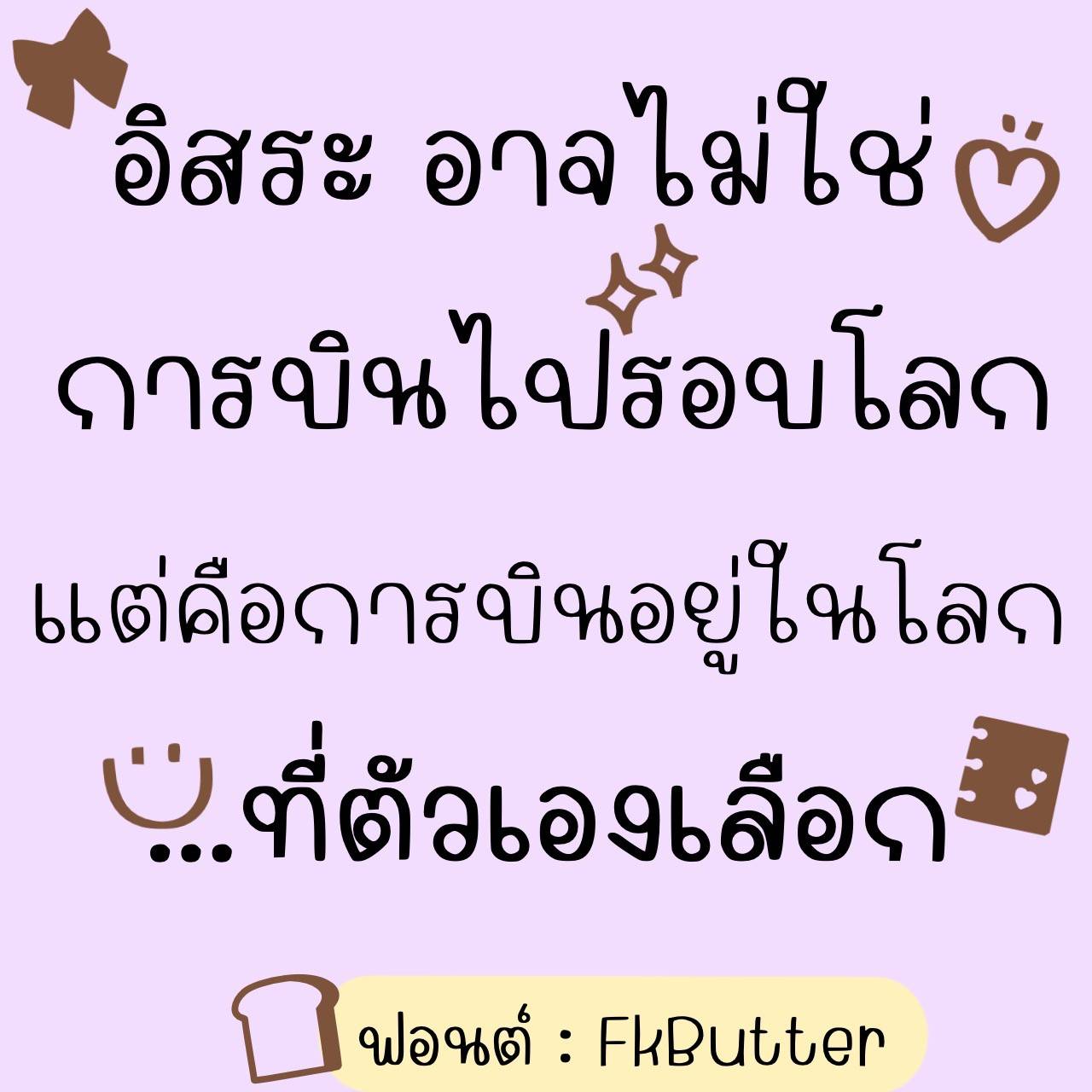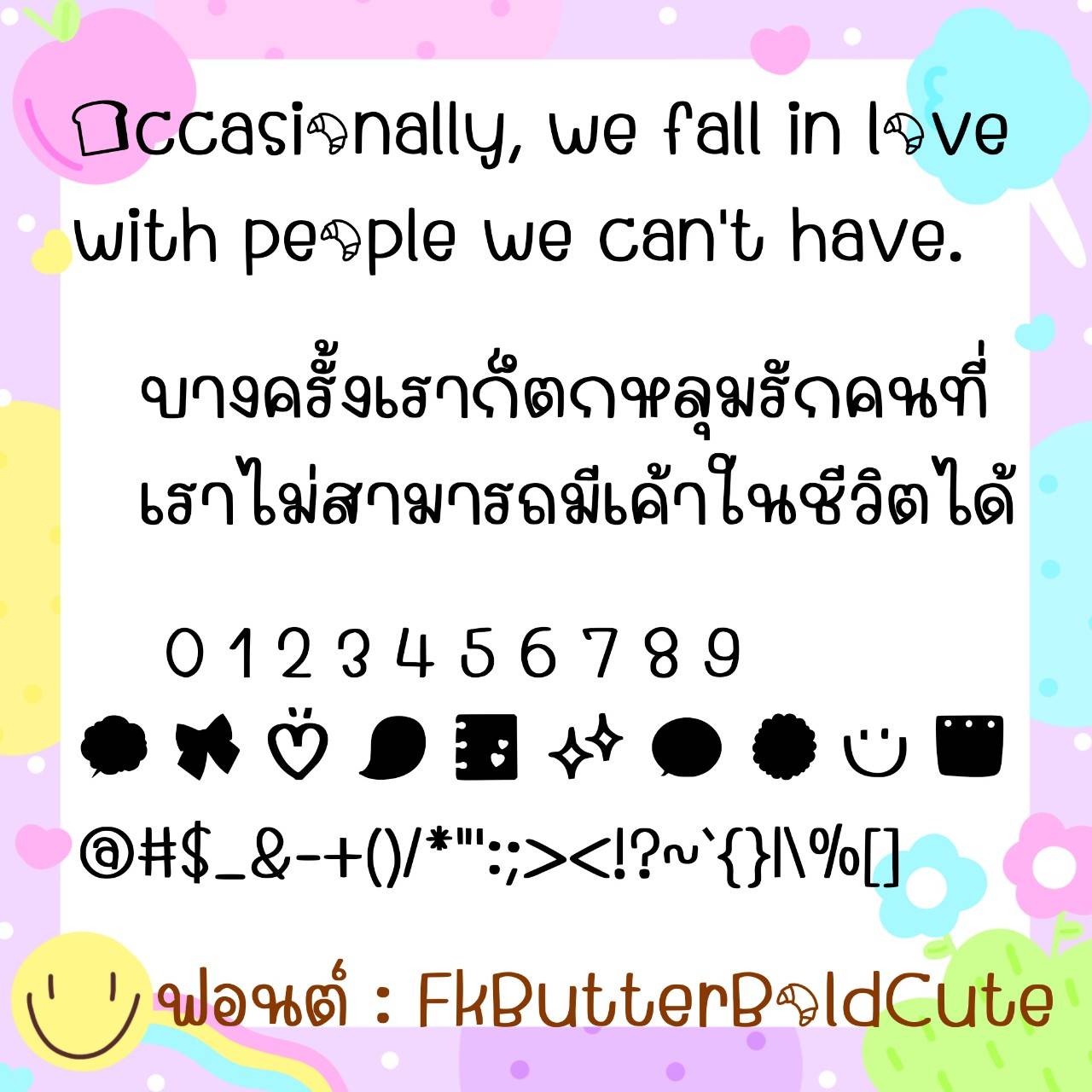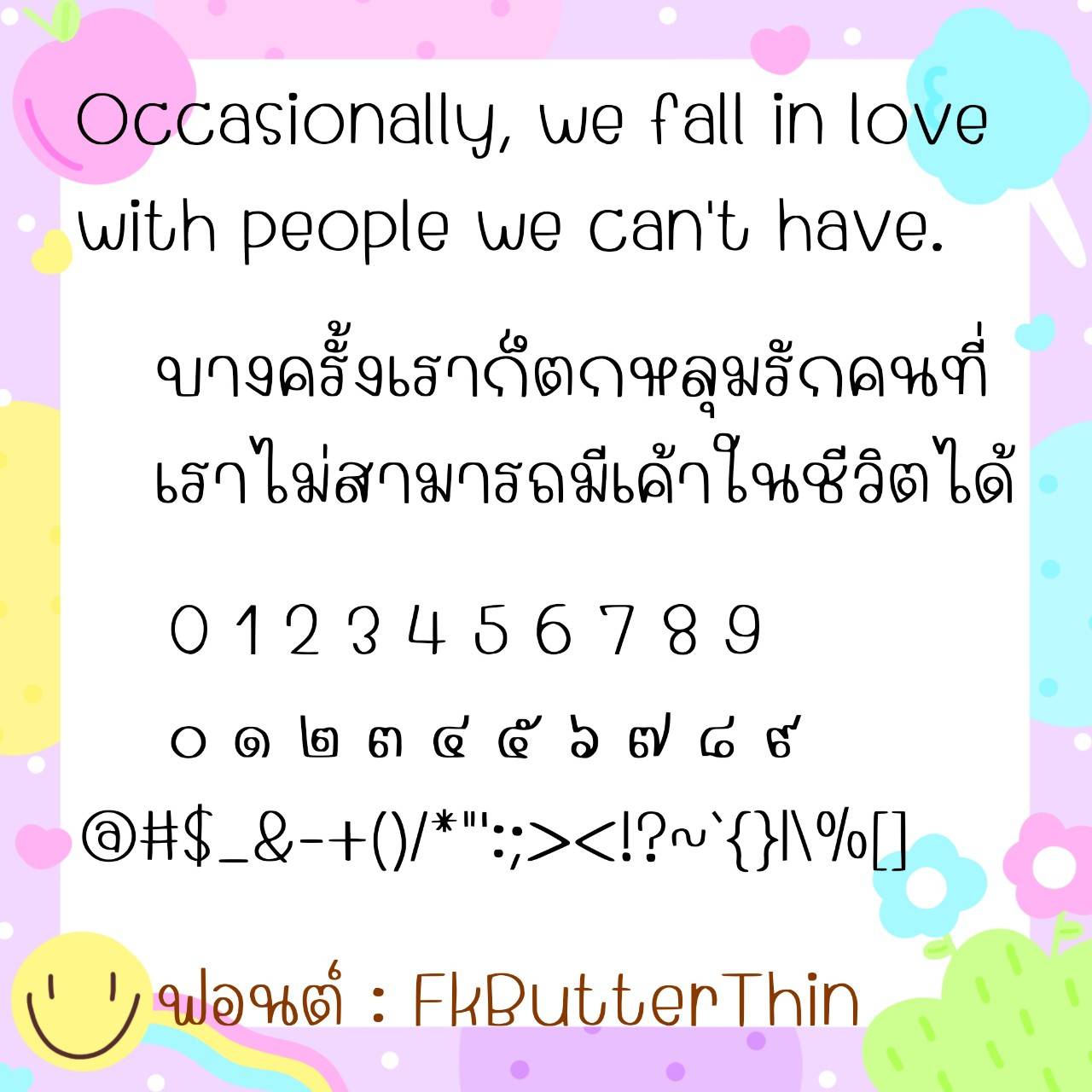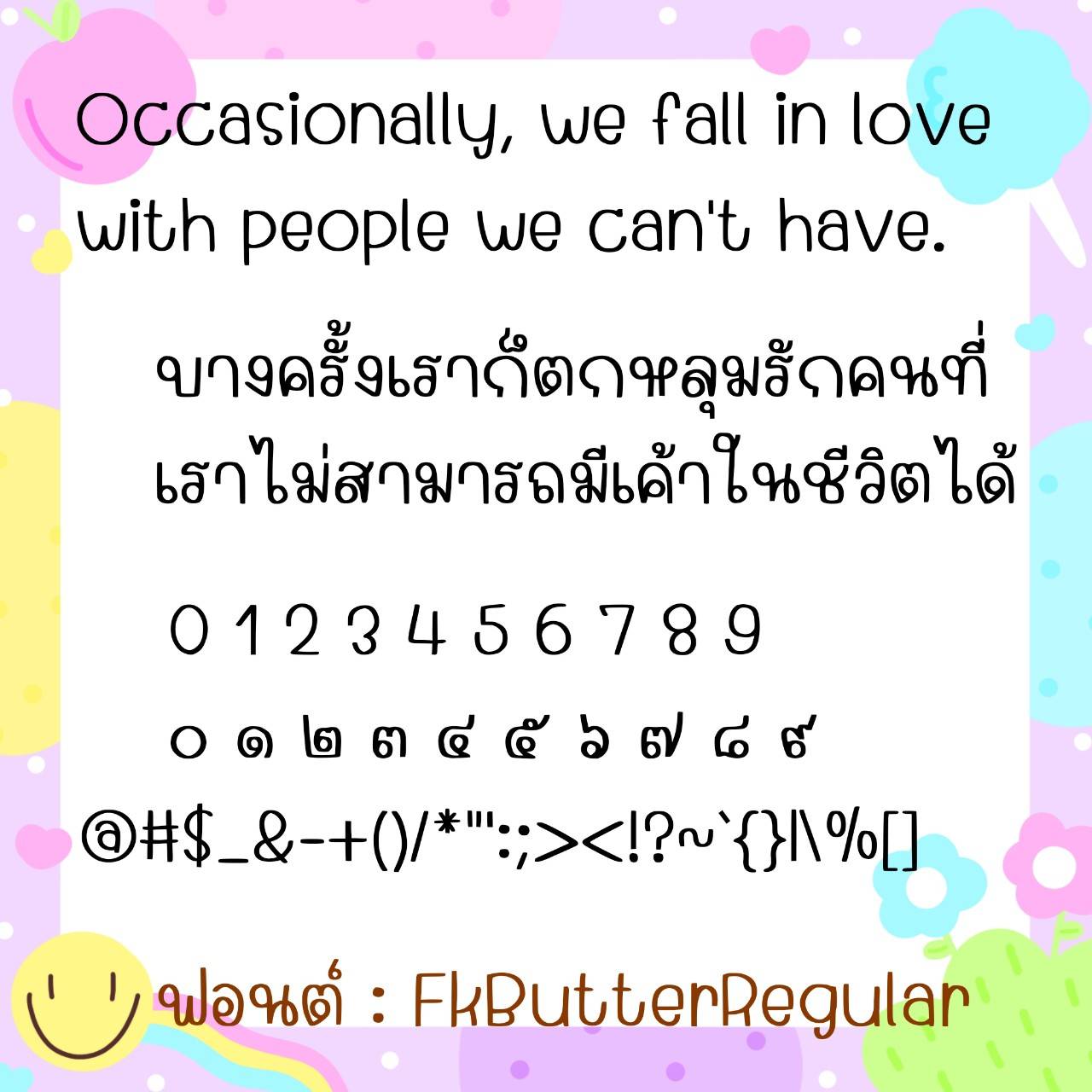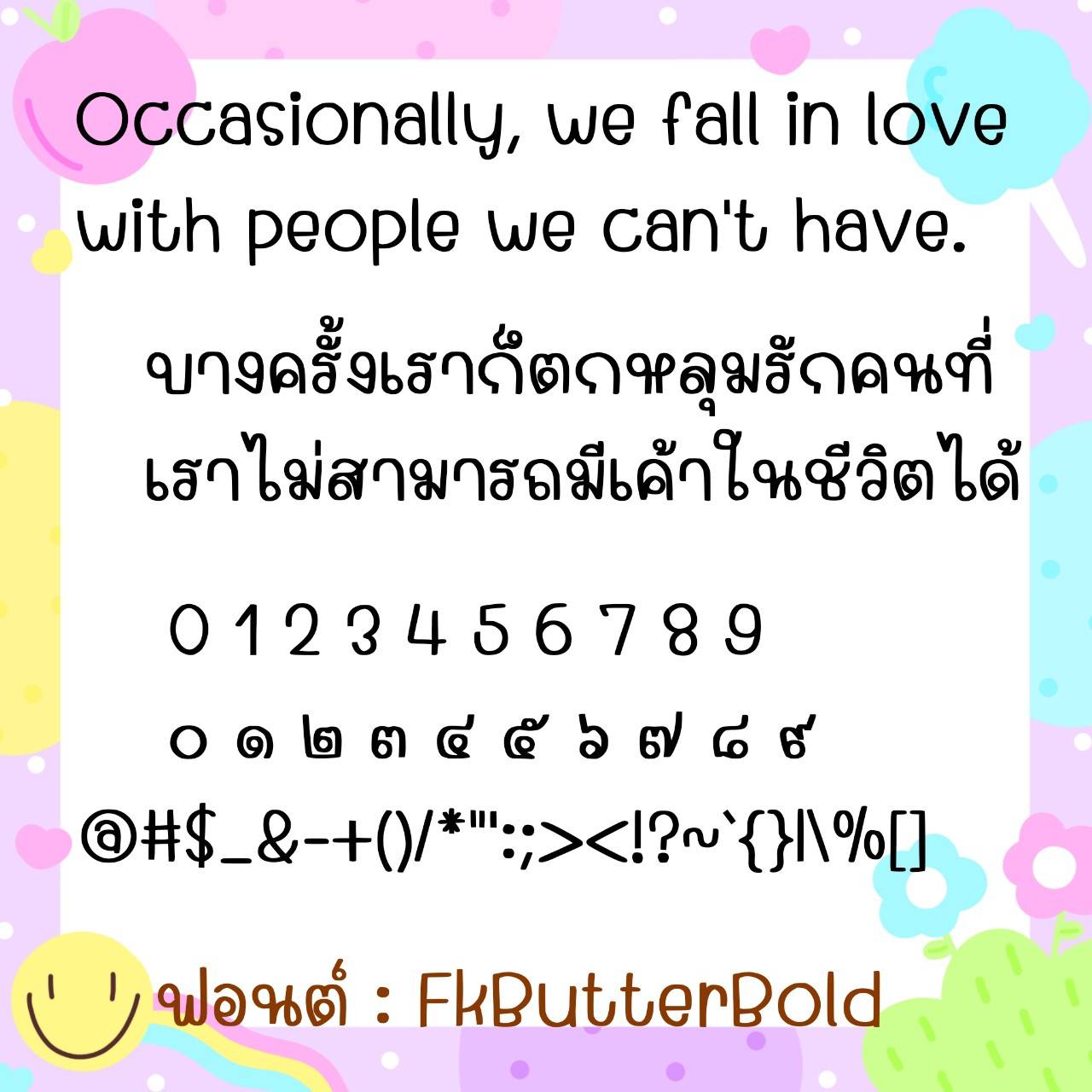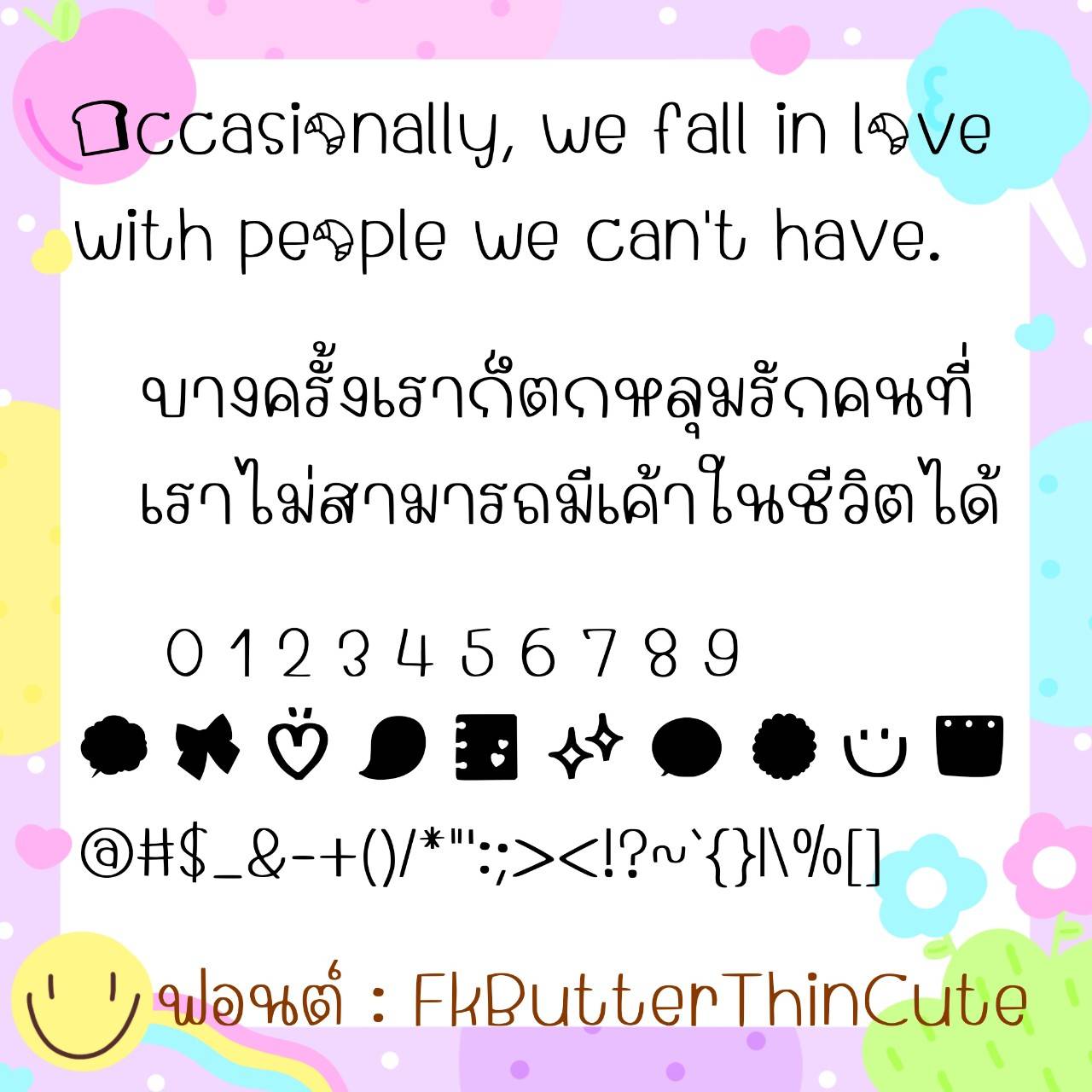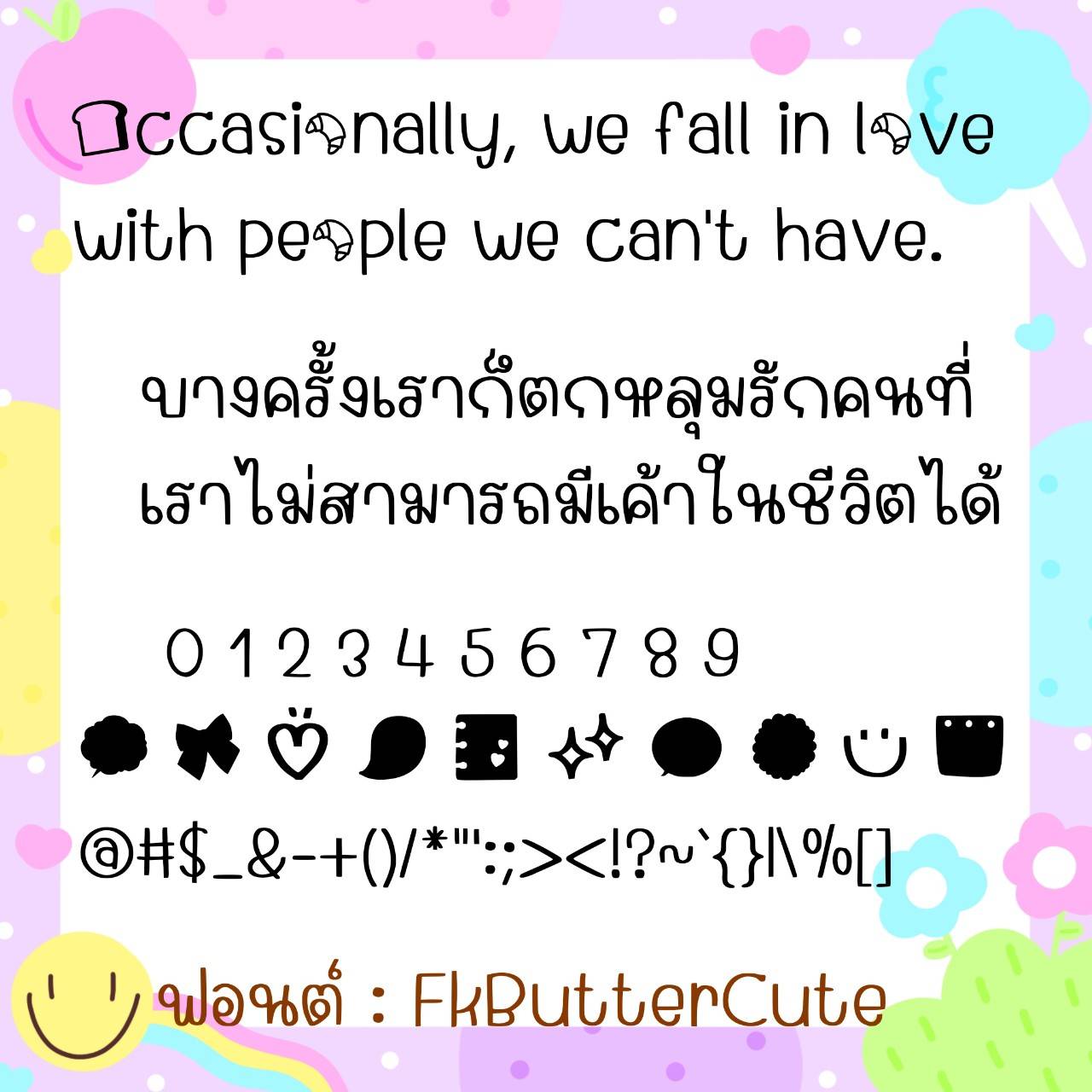
Font FkButter
ชื่อสินค้า : Font FkButter 💚
🔸ฟอนต์ลายมือหัวโต ตัวอ้วนกลม ดูน่ารักอ่านง่าย สไตล์วัยรุ่น ดูไม่น่าเบื่อ และยังมีไฟล์อิโมจิน่ารักๆที่ใช้แทนเลขไทยให้ในชุดด้วยค่ะ 🥰💙
🔹Big head handwriting font, chubby and round, looks cute, easy to read, youthful style, doesn’t look boring. And there is also a cute emoji file that can be used to replace Thai numbers in the set. 🥰💙